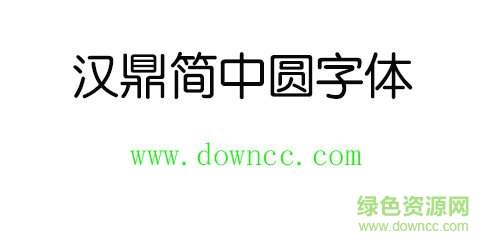
漢鼎簡(jiǎn)中圓是一款比較圓潤(rùn),又不是太粗的藝術(shù)字體,看起來(lái)非常的不錯(cuò)喲,讓喜歡用藝術(shù)字設(shè)計(jì)圖片或者其它設(shè)計(jì)的朋友能夠多一項(xiàng)選擇哦,讓你所設(shè)計(jì)的圖片也非常的亮眼,有需要的朋友趕緊來(lái)綠色資源網(wǎng)下載吧!